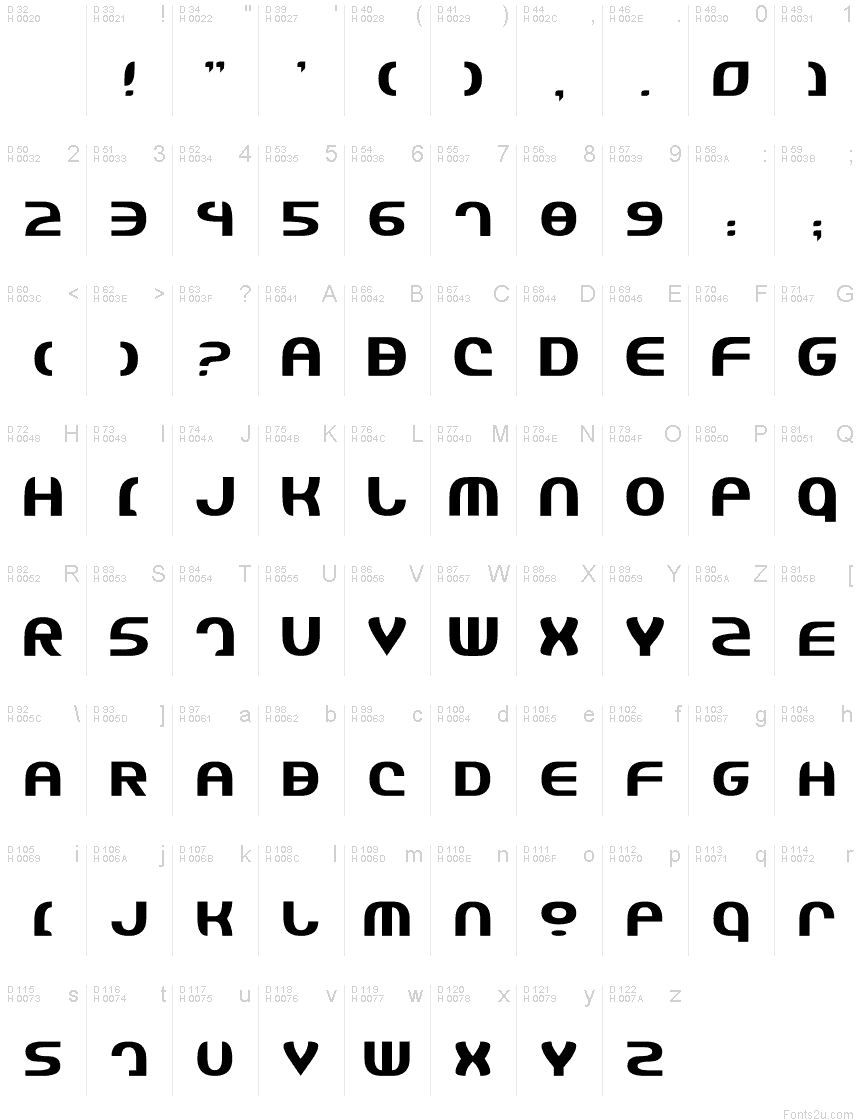
Jannisary Shield von Iconian Fonts ist eine kostenlose, moderne Display-Schrift mit einem markanten, röhrenartigen Rhythmus, der sowohl industriell als auch elegant wirkt. Ihre hohen, abgerundeten Striche und die kompakte Strichstärke verleihen jedem Wort eine robuste, schildartige Präsenz, während die quadratischen Abschlüsse für eine klare Textur sorgen, die nie comichaft wirkt. In großen Größen wirken die glänzenden, rohrförmigen Kurven fast dreidimensional und ziehen die Blicke auf sich, ohne überladen oder gekünstelt zu wirken.
Mit Jannisary Shield erhalten Überschriften sofort eine technologische Sci-Fi-Note, die sich hervorragend für Spieletitel, E-Sport-Branding, Filmplakate, Event-Grafiken und futuristische Produktlogos eignet. Diese kostenlose Schrift glänzt auch bei Interface-Überschriften und markanten Wortmarken, bei denen eine starke, einheitliche Silhouette gefragt ist. Kombinieren Sie Jannisary Shield am besten mit einer schlichten, geometrischen serifenlosen Schrift für den Fließtext und wählen Sie für Jannisary Shield ein oder zwei Nummern größer als üblich, um die geschmeidigen, gepanzerten Kurven perfekt zur Geltung zu bringen.